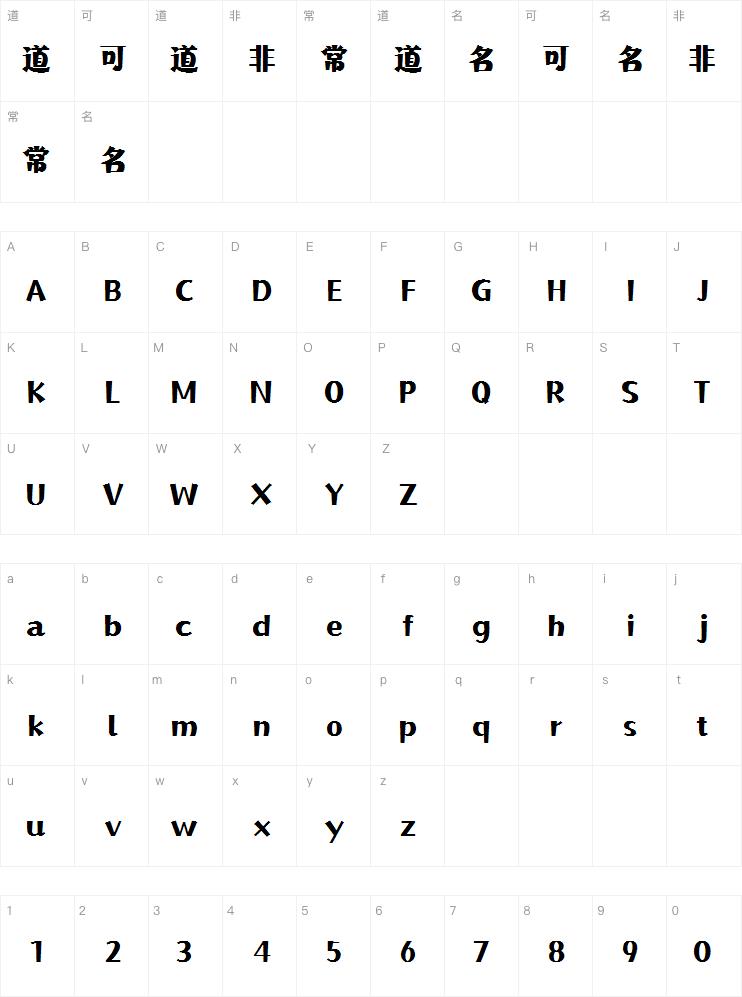
山海好运黑w
山海好运黑,是一款全新的字体,包含汉字9169个,符号200+个。该字体是一款综艺标题黑体字体,是一款具有强劲视觉冲击力的综艺风格标题字体。字形充实填满整个字框,造型硬朗,直线与弧线的笔画构成交相呼应;同时各种弧线的广泛应用,使得字形带有律动感,带来强有力的视觉冲击效果。该字体在综艺体的基础上做了诸多创新,使得该字体既有着流动的美感,又有着端肃的凝重,在正式用字场合落落大方,在日常使用环境中不失亲切友好,能够在保留综艺体基本特征的基础上更能适应当下时尚潮流的需要,助力各大新产品夺取标题主战场。
山海好运黑w